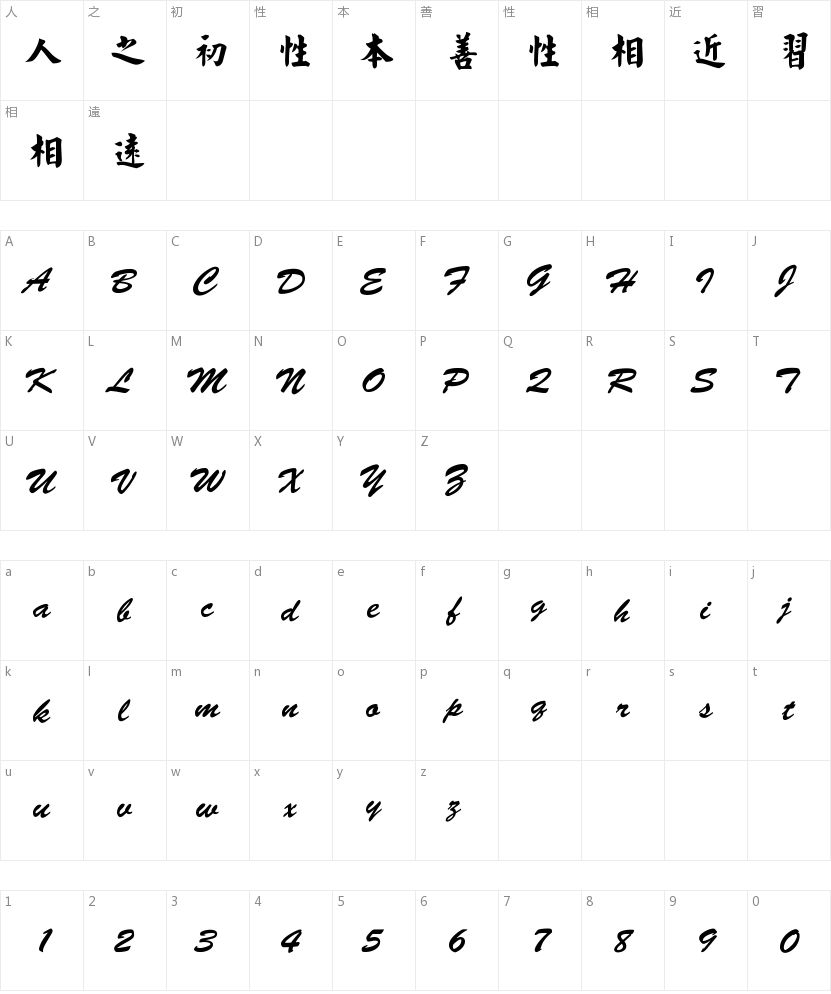
书法家行楷体
书法家行楷体是一种行书字体,它的特点是字形结构简单、笔画多,把笔画结合在一起,形成一个完整的字体。书法家行楷体的字体特点是字母的笔画简洁而又动感,更能体现出书法家个性化的风格。书法家行楷体的字体也适合在报纸、杂志等出版物中使用,可以给读者带来更多的视觉享受。
书法家行楷体是一款非常不错的手写艺术字体,具有很好的视觉感,适合于文化类的宣传设计、商业类品牌的广告和产品包装设计以及个性化文字排版等较多场景。